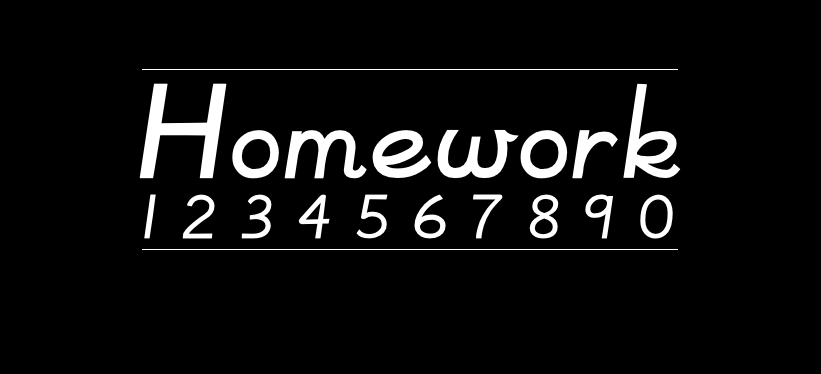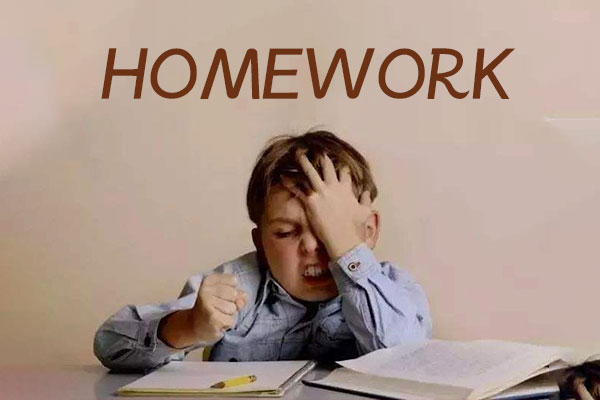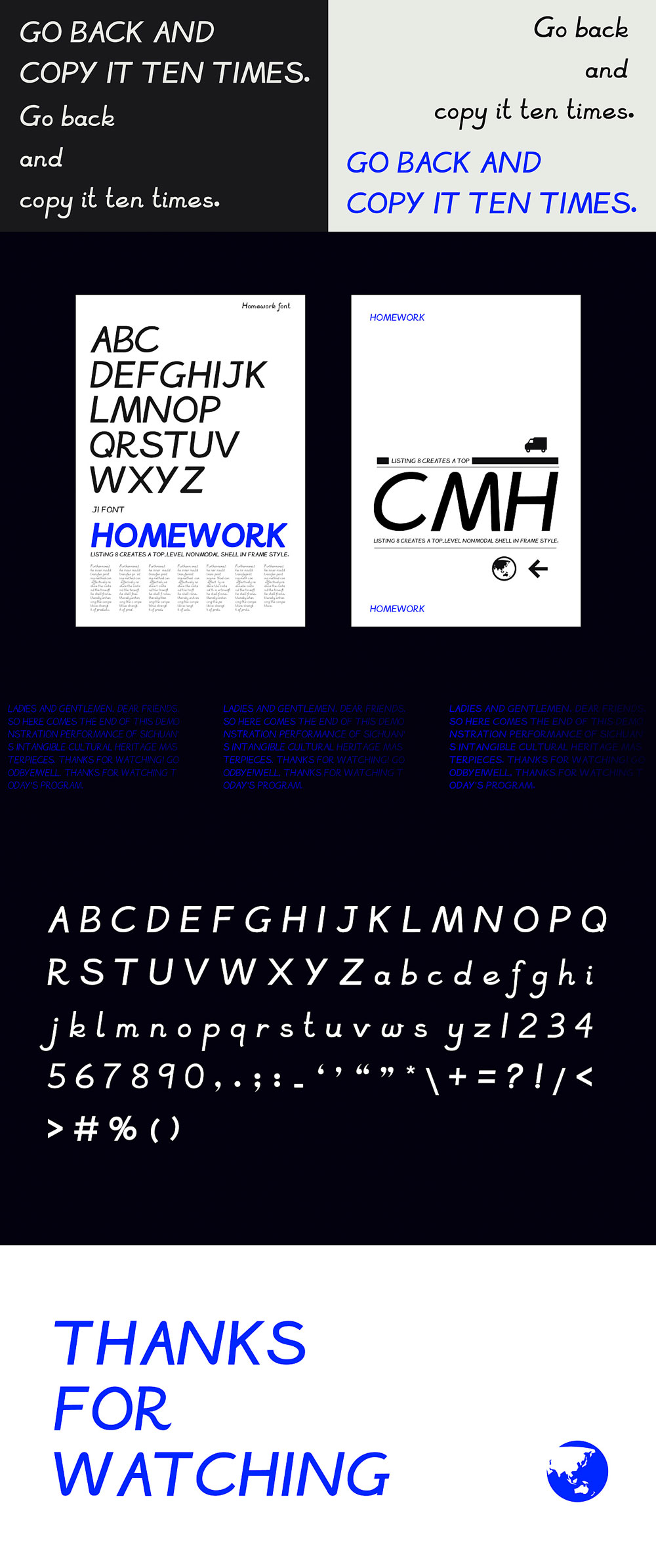
Homework
Homework的作者是来自中国湛江的学生叶伟鹏(特立独行的小鹏),这是一款英文字体,该字体是小鹏的第二款字体,灵感来源于小时候作业本上的英文单词和句子,还记得那首“拼音字母歌”,“abcdefg hejklmn opq rst uvw xyz”旋律依旧熟悉难忘。
该字体包含3字重,适合多种场合使用,字体首发于站酷,作者声明免费商用。